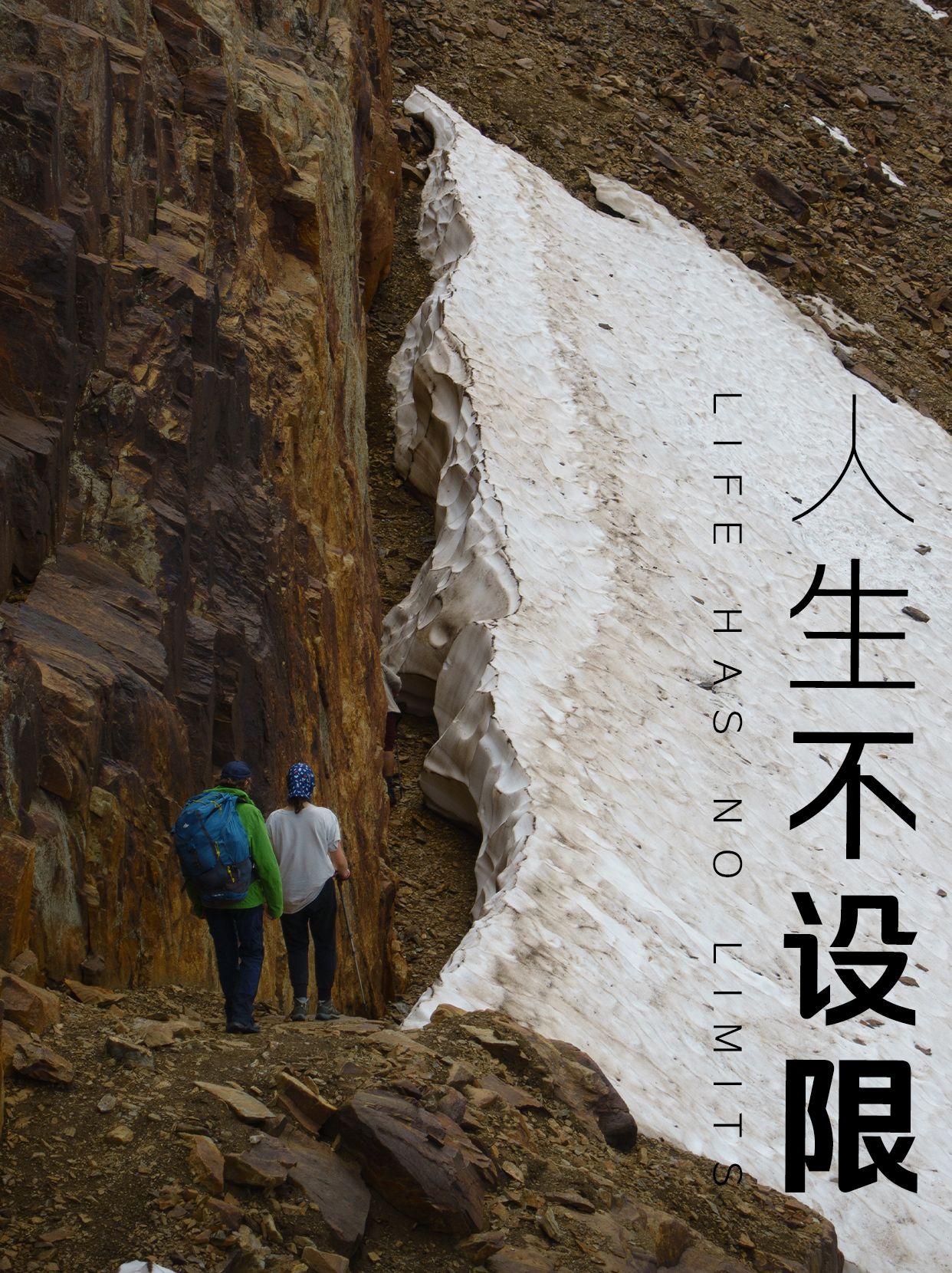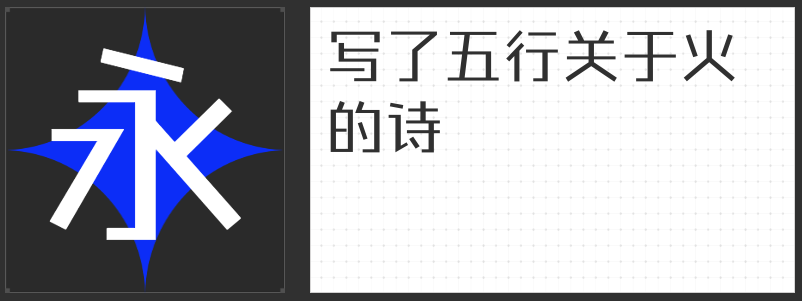
游戏UI字体的精选推荐
在游戏开发中,UI字体不仅是文字的载体,更是游戏画面与氛围的重要组成部分。合适的字体选择能显著提升游戏的整体视觉效果,增强玩家的沉浸感和体验。以下是一些精选的游戏UI字体推荐。
励字志向黑简 中粗以其独特的笔画设计和适中的粗细度,在游戏UI中展现出非凡的力量感与视觉冲击力。其字形结构稳健,线条流畅而富有张力,既保留了黑体字的稳重与大气,又融入了现代简约的审美理念,使得每一个字符都充满了活力与动感。
励字志向黑简 中粗还具有良好的可读性和兼容性,能够在不同尺寸和分辨率的屏幕上保持清晰的显示效果,确保玩家在各种游戏环境中都能获得良好的阅读体验。
励字造梦简 常规以其清新脱俗、温婉雅致的风格,在游戏UI设计中独树一帜。这款字体每一笔一划都透露着柔和与宁静,仿佛能引领玩家进入一个远离尘嚣、充满想象与创造的空间。其字形简约而不失细节,线条流畅而富有韵律感,既保留了传统书法的韵味,又融入了现代设计的简洁与明快。
此外,励字造梦简 常规还具备良好的可读性和适应性,能够在不同大小和分辨率的屏幕上保持清晰易读,确保玩家在任何游戏环境中都能轻松获取所需信息。
励字超级勇士简 常规,这款字体不仅适用于战斗场景,更能在角色对话、任务描述中彰显游戏世界的深度。其独特风格能迅速吸引玩家注意,提升游戏沉浸感。无论是史诗级战役还是细腻剧情,励字超级勇士简 常规都能完美融入,为游戏增添一抹不可多得的英雄色彩。
在游戏UI设计中,一款稳重而不失格调的字体能够显著提升游戏界面的质感。励字钧线黑简 常规以其独特的线条感和均衡的字体结构,成为游戏UI中的稳重之选。这款字体线条流畅,黑体风格赋予其强烈的视觉冲击力,同时又不失细腻与精致。无论是作为游戏标题、菜单选项还是信息提示,励字钧线黑简 常规都能展现出游戏的专业与高端。它不仅能够吸引玩家的注意力,还能在无形中增强游戏的整体氛围,让玩家沉浸于游戏世界之中。
总之,合适的游戏UI字体对于提升游戏体验至关重要。通过选择精选的字体,可以为游戏界面增添独特的视觉效果和风格特点,让玩家在游戏中获得更加炫酷和沉浸式的体验。无论是复古的像素风,还是科幻的未来感,亦或是艺术的手绘风,总有一款字体能完美匹配你的游戏风格。